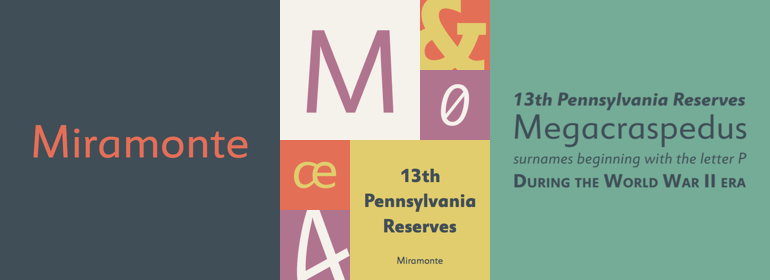
Miramonte™
Miramonte™,这款字体结构工整、笔画清晰,兼顾美观与易读性,适用于标题、正文、海报、包装、LOGO 等多种场景。字形优雅稳定,风格百搭耐看,适配日常排版与创意设计,让文字呈现更舒适、更具质感。Miramonte™一笔一画,皆是细节,以均衡的比例、流畅的线条打造舒适视觉体验,字形端正大气,风格简约现代。无论是商业设计、品牌宣传还是日常排版,都能轻松驾驭,让文字更有格调与力量。Miramonte™字体下载。
字体品牌: Ascender(Monotype) 设计师:Matteson,Steve 字体分类:衬线体 字体属性:外文 字符集:Unicode 发布时间: 2018